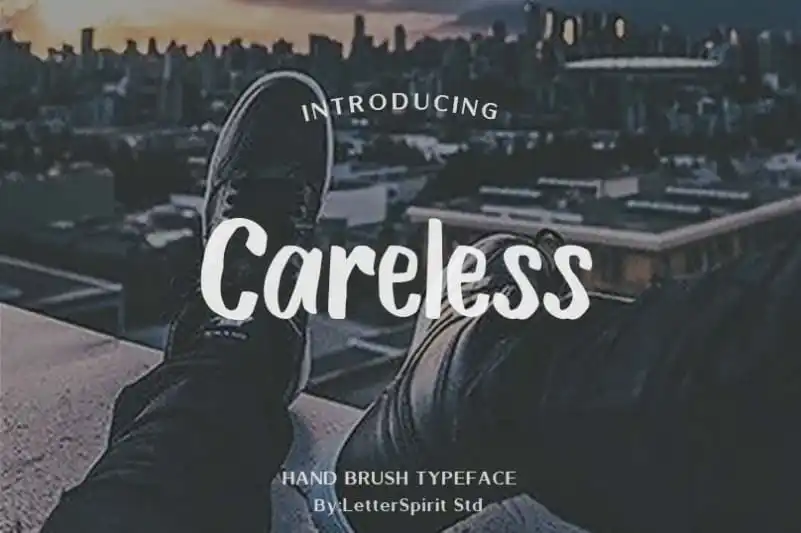
Careless Brush Font – Download Grátis
Careless Brush Font é uma elegante escolha para aqueles que buscam algo mais casual e despojado em suas aplicações digitais. Com linhas naturais e brilho único, essa fonte é um autêntico retrato da escrita manual em estilo de tijolos-marcadores. Ela traz um toque peculiar, revelando sua verdadeira essência como uma combinação única de letras cursivas personalizadas que inclui números e caracteres especiais. Esses detalhes adicionados podem dar ao seu texto um caráter único e um fluxo atraente, tornando cada mensagem original. Ideal tanto para projetos pessoais quanto comerciais, Careless Brush Font está aqui para trazer uma cara diferente à sua tipografia.